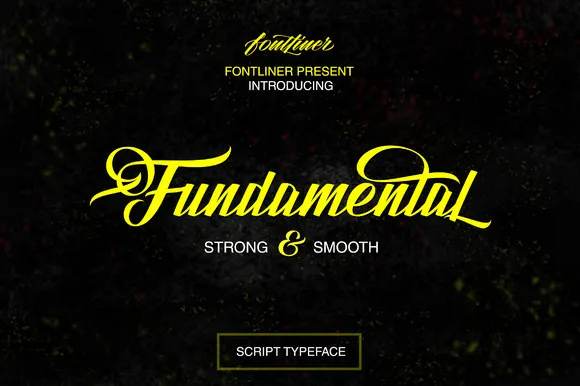
A fonte ‘Fundamental Font’ é uma fonte script que combina os elementos fortes com a suavidade perfeita para criar texto belo e elegante. Ideal para seu branding, logomarca, cabeçalho, cartazes, roupas, embalagens, cartões de visita e muito mais. Com ‘Fundamental Font’, você pode adicionar um toque único e sofisticado a qualquer projeto gráfico. Esta font é perfeita para quem busca uma solução versátil que atende a vários requisitos designísticos em uma só fonte. Ideal tanto para designers como para freelancers, a ‘Fundamental Font’ oferece o equilíbrio necessário entre força e facilidade de uso, tornando-a uma escolha ótima para qualquer projeto onde você deseja destacar seu trabalho com estilo e sofisticação.